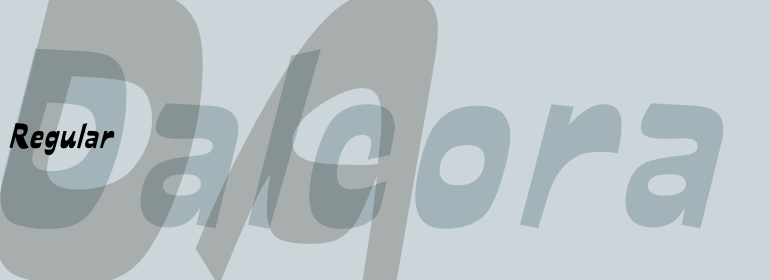
Dalcora™
字体品牌: Linotype(Monotype) 设计师:Koch,Erwin 字体分类:衬线体 字体属性:外文 字符集:Unicode 发布时间: 2018
Dalcora是由Erwin Koch于1989年设计的一款只有一个字重的字体。这种字体最显著的特点是它不同寻常的比例。文本字体的水平笔划通常都比垂直笔画更为精细,但Dalcora恰恰相反。 它略微偏向右侧,圆形的字母使该字体充满活力和欢快。Dalcora专门用于大尺寸的标题。
Dalcora was designed by Erwin Koch in 1989 in a single weight. The most distinguishing characteristic of this font is its unusual proportions. Text fonts are usually designed with more delicate horizontal strokes as the verticals, but Dalcora is exactly the opposite. Its slight slant to the right and the round forms of the letters make the font dynamic and cheerful. Dalcora is intended exclusively for headlines in larger point sizes.